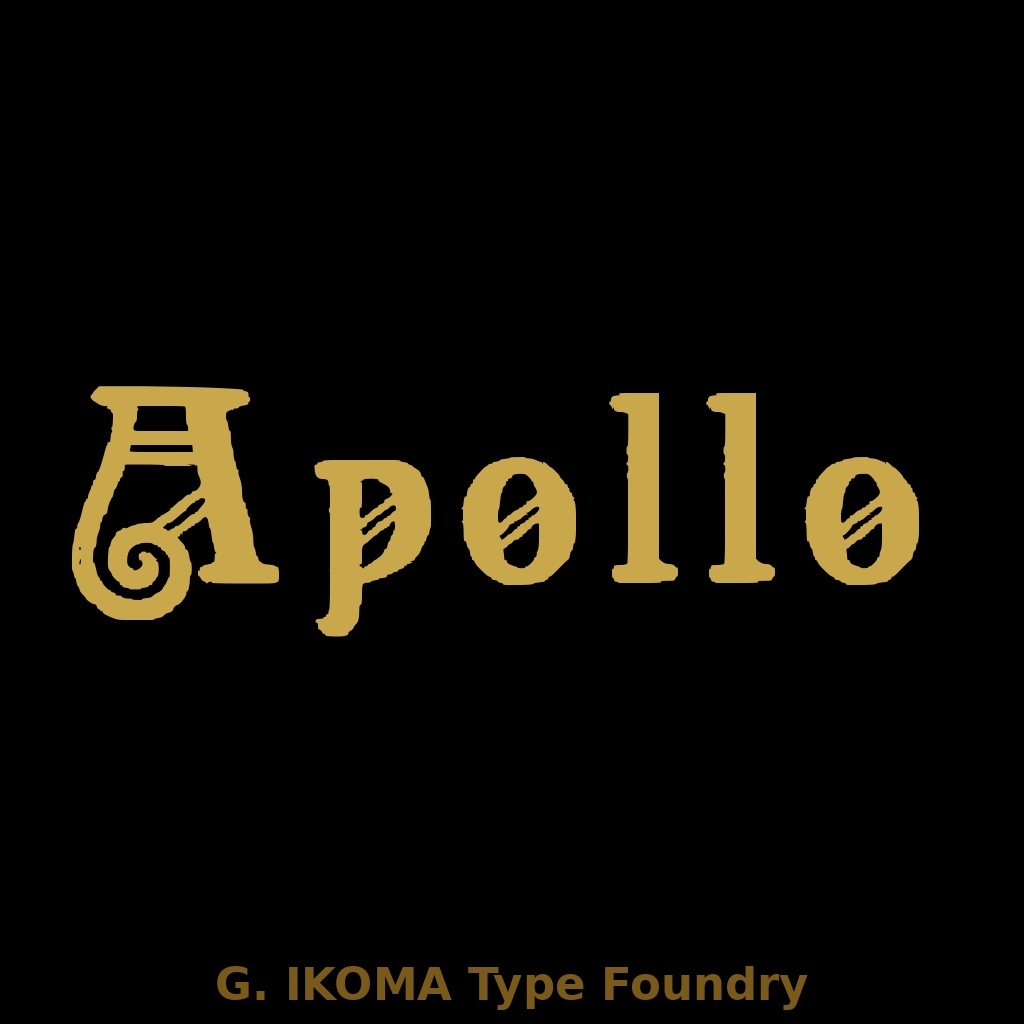
APOLLO — 19世紀欧州印刷資料復元フォント / Historical Revival Typeface [Jugendstil]
━━━━━━━━━━━━━━━━━━━━━━━━━━━━━ I Apollo G. Ikoma Archives — 欧文フォント ━━━━━━━━━━━━━━━━━━━━━━━━━━━━━ 19〜20世紀初頭のヨーロッパ活字見本帳を原典にデジタル復刻した欧文書体です。 スタイル:アールヌーボー / ユーゲントシュティール 【収録文字】 大文字(A–Z)/ 小文字(a–z)/ 数字(0–9)/ 記号・アクセント文字 総グリフ数:約134字 【収録ファイル】 ・I_Apollo_Extended.ttf(TrueType 拡張版) ・LICENSE.txt(使用許諾書) 【ライセンス】 個人利用・商用利用ともに使用可能です。 広告・印刷・WEB・映像・ロゴ・同人誌など幅広い用途にお使いいただけます。 フォントファイルの再配布・再販売、改変・派生フォントの公開は禁止されています。 詳細は同梱の LICENSE.txt をご確認ください。 【注意事項】 ・本フォントはデジタル復刻版です。原典活字の字形を忠実に再現していますが、 現代の標準フォントとは字形や文字間隔が異なります。 ・インストール方法はOSの標準フォントインストール手順に従ってください。 G. Ikoma Archives | ikoma1957@gmail.com